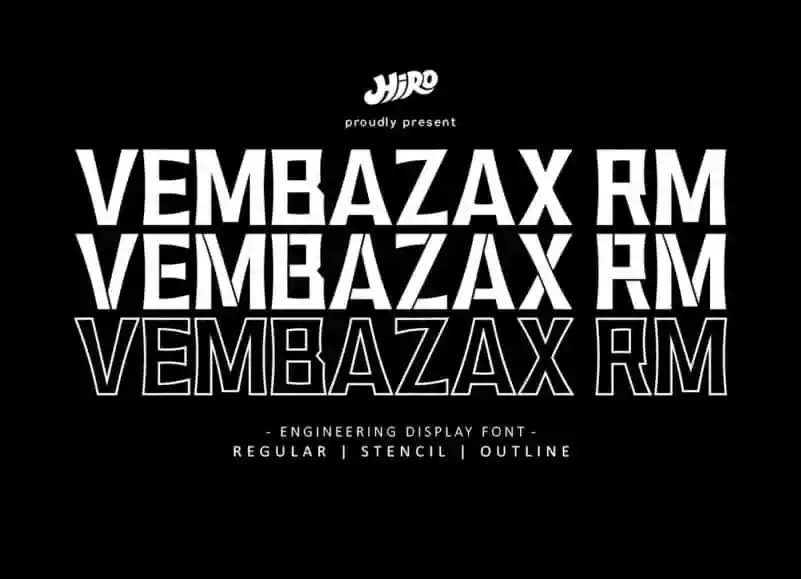
Vembazax RM Display Font – Download Grátis
A Vembazax RM Display Font é uma fonte futurista e tecnológica criada pelo designer Hiro std. Com três diferentes estilos únicos, ela oferece flexibilidade para criar designs de logotipos ou painéis publicitários. Esta fonte de exibição está disponível gratuitamente e traz um conjunto versátil de opções que inclui uma opção sólida com traços, outra sem traço e ainda mais uma versão stencil. Cada estilo vem com diversas ligaturas estilizadas que podem adicionar um toque especial ao seu design. Se você está procurando por uma fonte de exibição moderna e tecnológica para seus próximos projetos gráficos, a Vembazax RM Display Font é perfeita. Sua versatilidade permite combinar diferentes estilos para criar algo único e incrível.